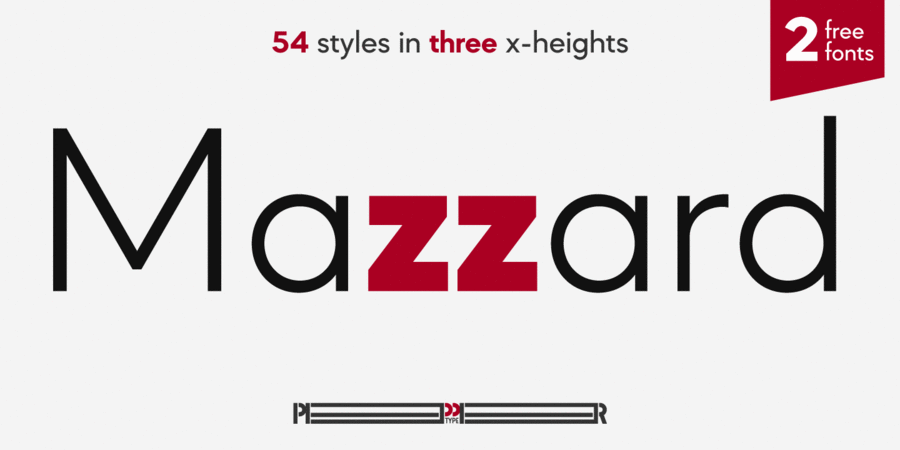
Mazzard H – частина шрифтового суперсімейства Mazzard з високим x-height. Суперсімейство складається з трьох геометричних гротесков з різною висотою рядкових знаків. Mazzard H має широкий спектр підтримки мов та пропонує великій вибір альтернативних гліфів. Шрифт розробив Олег Ліщук в 2019 році.
Асоціації з сімейством шрифтів Mazzard HОсобистість і характер гарнітури:
елементарний, мінімалістичний, точний, рівний, статичний, логічний, лаконічний, стійкий, автоматичний, штучний, холодний, інженерний, міський, різкий, чіткий, креслярський, чистий, сучасний, гострий, тонкий, дротяний, скляний, легкий, прохолодний, ясний, невагомий, прозорий, крихкий, модний, худий, технічний, стабільний, Простий, нейтральний, урбаністичний, зрозумілий, формальний, прагматичний, практичний, твердий, доступний, серйозний, надійний, впевнений, машинний, сильний, самостійний, переконливий, індустріальний, техногенний, обов'язковий, архітектурний, залізний, сталевий, міцний, авторитетний, важливий, мотивуючий, крутий, залізничний, солідний, відповідальний, амбітний, мужній, суворий, добротний, жорсткий, грубий, потужний, значний, товстий, яскравий, помітний, важкий, щільний, тісний, монументальний, активний, гучний, сміливий, пролетарський, крижаний